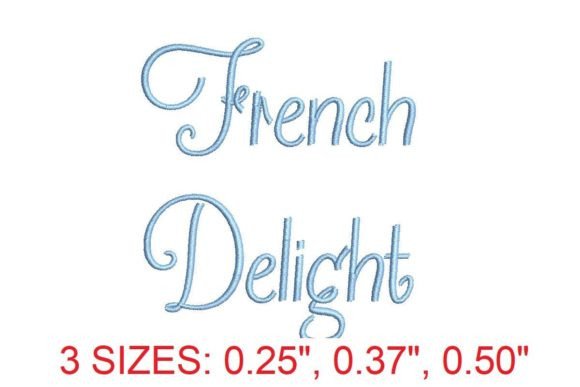
French Delight Embroidery Font
Doğru tasarım öğelerini bulmak zor olabilir, ancak French Delight Embroidery Font, çalışmanızı anında bir üst seviyeye taşıyan olağanüstü bir koleksiyon sunar.
Hassasiyetle hazırlanan French Delight Embroidery Font, temiz vektörler, pürüzsüz tipografi ve içinizin rahat etmesi için ticari bir lisans sağlar.
İster İsteğe Bağlı Baskı (POD) ürünleri, ister düğün davetiyeleri veya sosyal medya grafikleri oluşturuyor olun, French Delight Embroidery Font ideal bir uyumdur.